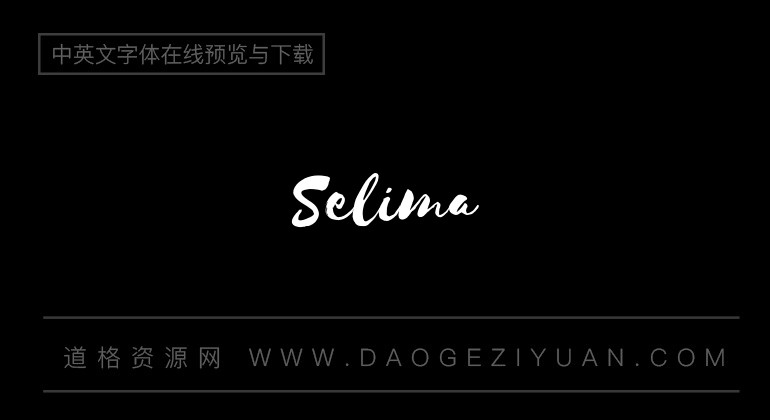
Selima
? Selima 字体是一款精致、时尚的英文字体,它由著名的设计师Eben Sorkin设计,具有柔和、温暖的氛围。Selima字体以清新的曲线、细腻的笔画和精致的线条为特色,它拥有大量的字形和字重,可以满足不同的设计需求。Selima字体适用于标题、标签、卡片、海报、书籍、杂志、网页等,是一款十分灵活的字体。
Selima是一款非常不错的手写艺术字体,具有很好的视觉感,适合于文化类的宣传设计、商业类品牌的广告和产品包装设计以及个性化文字排版等较多场景。
Selima字符映射图